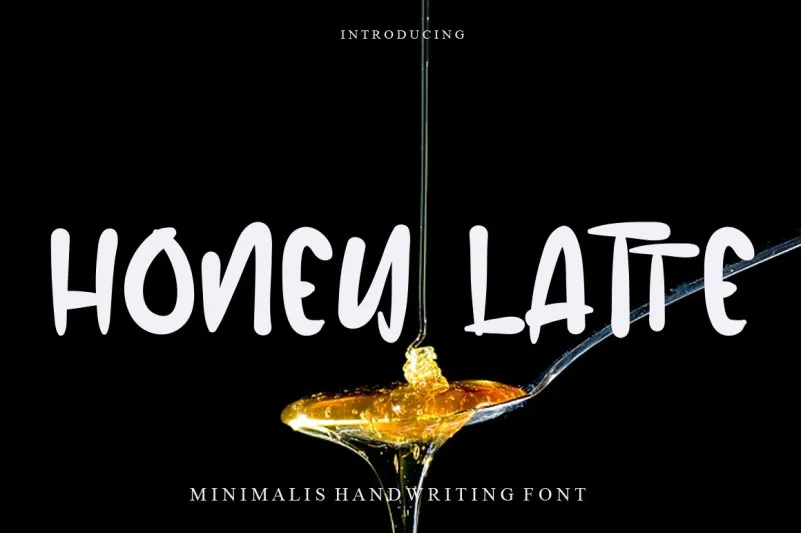
Esta é uma fonte à mão livre delicada, genuína e acolhedora. Ela se destaca por sua simplicidade suave e elegante que parece encaixar perfeitamente no trabalho de design de um grande número de ideias. Com este belo conjunto de letras manuscritas, cada projeto ganha uma pitada de alegria e romantismo. Seja para criar cartões de aniversário românticos ou ilustrações do cotidiano com toques divertidos, esta fonte será um elemento incrível que enriquece qualquer trabalho. Para você que gosta da simplicidade e do charme autêntico, a “Honey Latte Font” da LevinCreative é uma escolha inteligente para tornar seus trabalhos mais memoráveis.